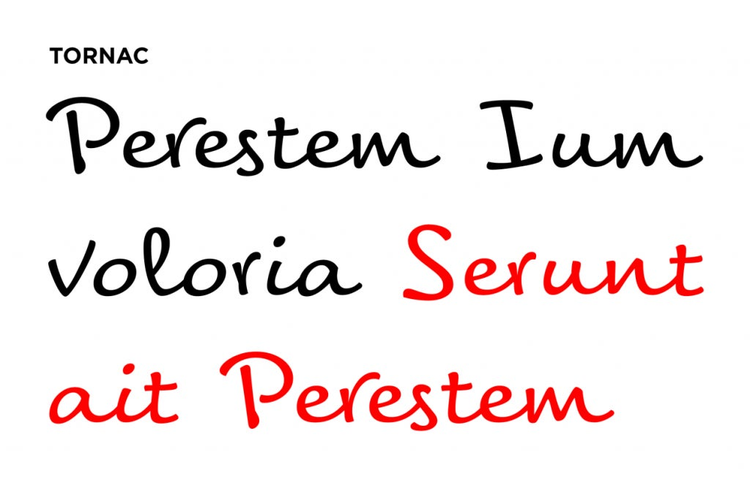
Du sollst also etwas gestalten. Vielleicht einen Flyer, der für das nächste Seminar deines Unternehmens wirbt. Oder Einladungen zur Hochzeit deiner Freundin. Du weißt jedenfalls, wie das Projekt aussehen soll. Wie der Text klingen soll, ist dir auch klar – aber aus irgendeinem Grund kommen deine Ideen im endgültigen Design nicht richtig zur Geltung.
Wenn dir das bekannt vorkommt, dann schau dir einmal deine Schriftarten an.
Was sind Schriftarten?
Wer jemals ein Textverarbeitungsprogramm verwendet hat, verfügt schon über Grundkenntnisse in den Schriftarten. Für Designprojekte, bei denen die Schriftart wesentlich zur Vermittlung der Botschaft beiträgt, musst du aber auch die Unterschiede zwischen Drucktypen, Schriftfamilien und Schriftart kennen.
- Drucktype ist die allgemeinste Bezeichnung für alles, was in der visuellen Gestaltung als Text erscheint. Der Begriff bezog sich ursprünglich auf die aus Holz oder Metall hergestellten Buchstaben (auch: Lettern).
- Typografie ist der von Grafikern verwendete Begriff zur Bezeichnung des Stils und Erscheinungsbilds von gedrucktem Text. Grafiker können sich auf Typografie, die Kunst der visuellen Gestaltung und Anordnung von Text, spezialisieren.
- Schriftfamilie oder Schriftbild bezeichnet ein vollständiges Alphabet, dessen Buchstaben und Symbole alle ähnlich gestaltet sind. Times, Arial und Minion sind Beispiele für Schriftfamilien.
- Schriftart bezieht sich auf den spezifischen Stil (oder Schriftschnitt) einer Schriftfamilie. Arial Black ist eine Schriftart der Schriftfamilie Arial. Minion Pro Italic ist eine Schriftart der Schriftfamilie Minion.
Der Begriff „Schriftart“ bezieht sich auf den spezifischen Stil (auch als Schriftschnitt bezeichnet) einer Schriftfamilie. Arial Black ist eine Schriftart der Schriftfamilie Arial und Minion Pro Italic ist eine Schriftart der Schriftfamilie Minion.
Warum sind Schriftarten so wichtig?
Man könnte meinen, es spielt keine Rolle, welche spezielle Schriftart man wählt, solange die Leser die Informationen nur entziffern und verstehen können. Doch mit der Gestaltung des Texts anhand des Drucktyps lassen sich Wirkungen erzielen, die über die simple Verbreitung der schriftlichen Nachricht hinausgehen. Schriftarten leisten tatsächlich einen großen Beitrag dazu, den Stil deiner Arbeit zu definieren und eine solide Markenidentität zu schaffen.
Josh Baron, Multimedia Art Director der Agentur für Markenführung Sparxoo, erklärt es so: „Die Wahl der Schrift ist von entscheidender Bedeutung. Die Typografie ist für eine Marke genauso wichtig wie alle anderen Elemente der Markenidentität. In vielen Fällen transportiert sie die Markensprache.“
Unterschiedliche Schriftarten lösen beim Betrachter unterschiedliche Gefühle aus. Mit der Wahl deiner Schrift kannst du schon den Kern deiner Botschaft vermitteln, bevor die Betrachter auch nur ein Wort des Textes gelesen haben. Du kannst dein Design durch die Schrift mit visuellen Stilnuancen aufpeppen, die Aufmerksamkeit erregen und die Gestaltung bereichern. In die Auswahl geeigneter Schriftarten solltest du daher genauso viel Energie investieren wie in das übrige Design.
Wie wähle ich die richtige Schriftart?
Sehen wir uns kurz die Fachbegriffe an. Grundsätzlich werden bei den Schriftarten zwei Stile unterschieden: Serifenschriften und serifenlose Schriften. Serifen sind die feinen Linien, die einen Buchstabenstrich unten abschließen.
- Calibri ist eine serifenlose Schriftart.
- Cambria ist eine Serifenschrift.
Im modernen Design sind für Fließtext sowohl Serifenschriften als auch serifenlose Schriften akzeptabel. Egal, wie du dich entscheidest, achte darauf, eine einfache Schriftart zu verwenden, die gut lesbar ist. Bevor du endgültig deine Wahl triffst, solltest du vom Computer zurücktreten und überprüfen, ob die Schriftart mühelos zu lesen ist. Bei Druckprojekten druckst du dir am besten Beispiele der Schriftarten deiner engeren Wahl aus und siehst dir an, wie gut sie auf Papier lesbar sind. Einige Schriftarten kannst du auf einem Poster in voller Größe besser lesen als auf dem Bildschirm.
Man muss „testen und schauen“, wie Dan Rhatigan, Senior Manager im Adobe Type Team, es ausdrückt. „Es bringt nichts, eine Schrift nur deshalb zu wählen, weil sie einen schicken Namen hat oder bestimmte Gimmicks, die einem gefallen. Am besten probiert man mehrere Schriften aus, findet heraus, wie sie sich zum übrigen Design verhalten, und vergleicht die Ergebnisse.“
Experimentiere ruhig mit verschiedenen Schriftarten, vor allem, wenn du noch nicht viel Erfahrung im Grafikdesign hast. Manchmal weiß man erst, was gut wirkt, wenn man es auf der Seite sieht.
Wie viele verschiedene Schriftarten dürfen es sein?
Einer der wichtigsten Tipps für ein stimmiges Design lautet: Verwende in einem Projekt nie mehr als zwei oder drei Schriftarten. Zu viele Unterschiede bei den Schriftarten für die verschiedenen Abschnitte lenken den Leser nur ab und verwirren ihn.
Für die Wahl deiner Schriftarten gelten dieselben Grundprinzipien wie für jedes andere Gestaltungselement auch, zum Beispiel Kontrast und Wiederholung. Wenn du mehrere Schriftarten verwenden willst, sollten sich diese so stark unterscheiden, dass sie einzelne Informationen voneinander abheben, aber dennoch visuell gut zusammenpassen.
Text ist ein wesentliches Element für den Gesamterfolg deines Projekts. Wenn du die ideale Schriftart gefunden hast, wirst du Aufmerksamkeit erregen, deine Botschaft klar vermitteln und deine Marke gekonnt ins rechte Licht rücken. Fange gleich an mit der Liste unserer Lieblingsschriftarten und synchronisiere sie mit deiner Design-App.